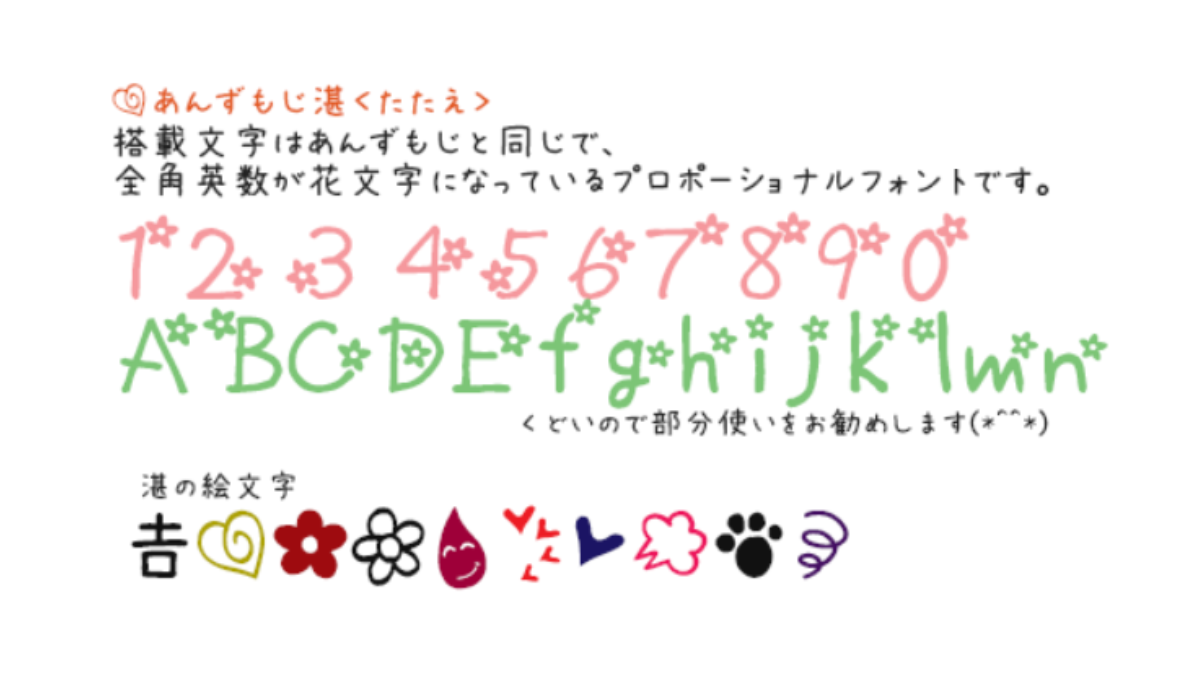
あんずもじ湛(たたえ)は、女性らしい手書き風の縦書きにも対応した日本語フリーフォントです。全角英数が花文字になっています。プロポーショナルフォントのみ収録。
| 書体名 | あんずもじ湛 |
| 書体 | 手書き風 |
| 収録文字 | アルファベット カタカナ ひらがな 数字 漢字 絵文字 記号 |